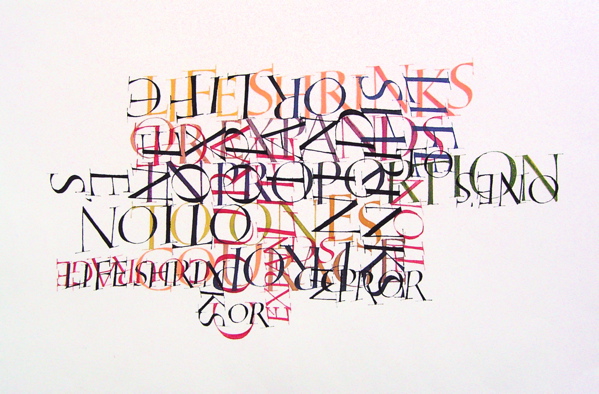
重ねて書く
ガッシュで文字を重ねて書いて行くと、ガッシュの上に書いた文字は、ぼややんと太い線になってしまいますよね。ガッシュonガッシュで細い線は不可能です。
こんな風にどんどん書いて行きたい時には、どうしましょう。
ガムサンダラックですか?
確かに細い線がは書けますが、何度も重ねていくと、ペン先に粉こなが入ってしまって、いちいち洗わないとならず面倒です。
この場合はフィクサチーフをかけながら書いていきました。
でも、もうこのあたりが限界。どんどかけて行きますので、徐々にしっかりかかってしまう部分が増えて行き、そうなると、最後ははじきすぎて文字がのらなくなります。
じゃあ、どうしましょう。
いろいろと試してみていますが、結論から言うと、いろいろ組み合わせがよさそうです。
まずガッシュにアクリル系のメディウムを入れて耐水性の絵の具にして書く。または、アクリル絵の具で書く。
その上にかる〜くささっとフィクサをかける。(アクリル系の絵の具の上は、細い線がやはり出にくいですからね)次はガッシュで文字を書く。
書いたらもう一回フィクサ。その上に今度もガッシュで文字を書いたら、今度はサンダラック。そして、またガッシュで文字を書いて、もう一度サンダラック。
たぶんこのあたりで、もう限界になると思います。はじいてしまうでしょう。
レイヤーの作品は、奥行きが作れるし面白い効果が出るのでやりたいですが、どこまでも美しい線を出すのは難しいです。
他にも方法はあるかも。
あ、そうそう水乾絵の具は、重ねても大丈夫でしたっけ!!文字を何度重ねてもきれいに書けたような気がします。ってことは、にかわがいいのかな?
試してみる価値ありそうですね。やってみませう